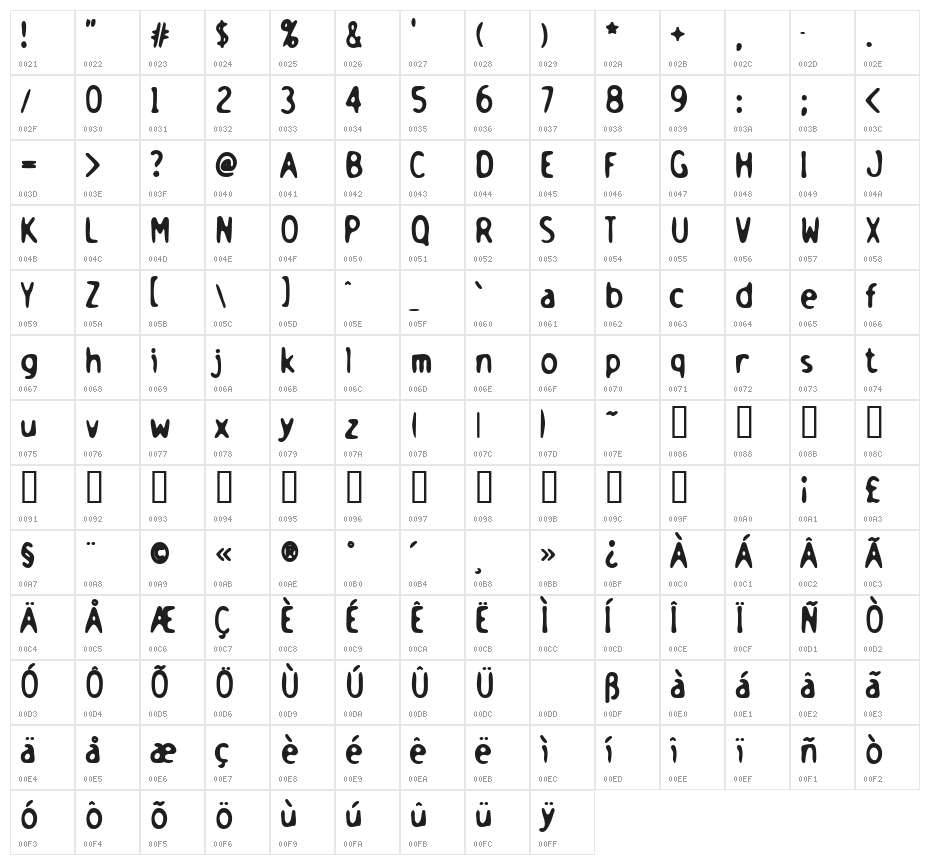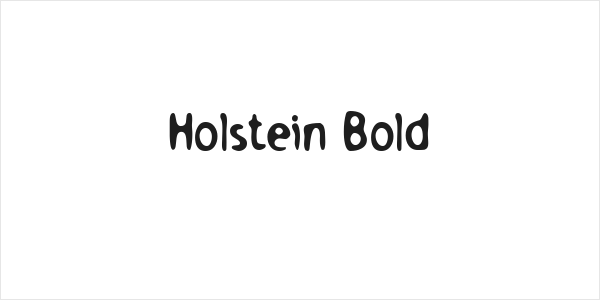
Holstein Bold Font
✎ Distorted Eroded
| Categorie | Distorted Eroded |
| Stile generale | Playful, Whimsical |
| Progetti proposti | Ideal for children's books, playful branding, posters, and creative design projects. |